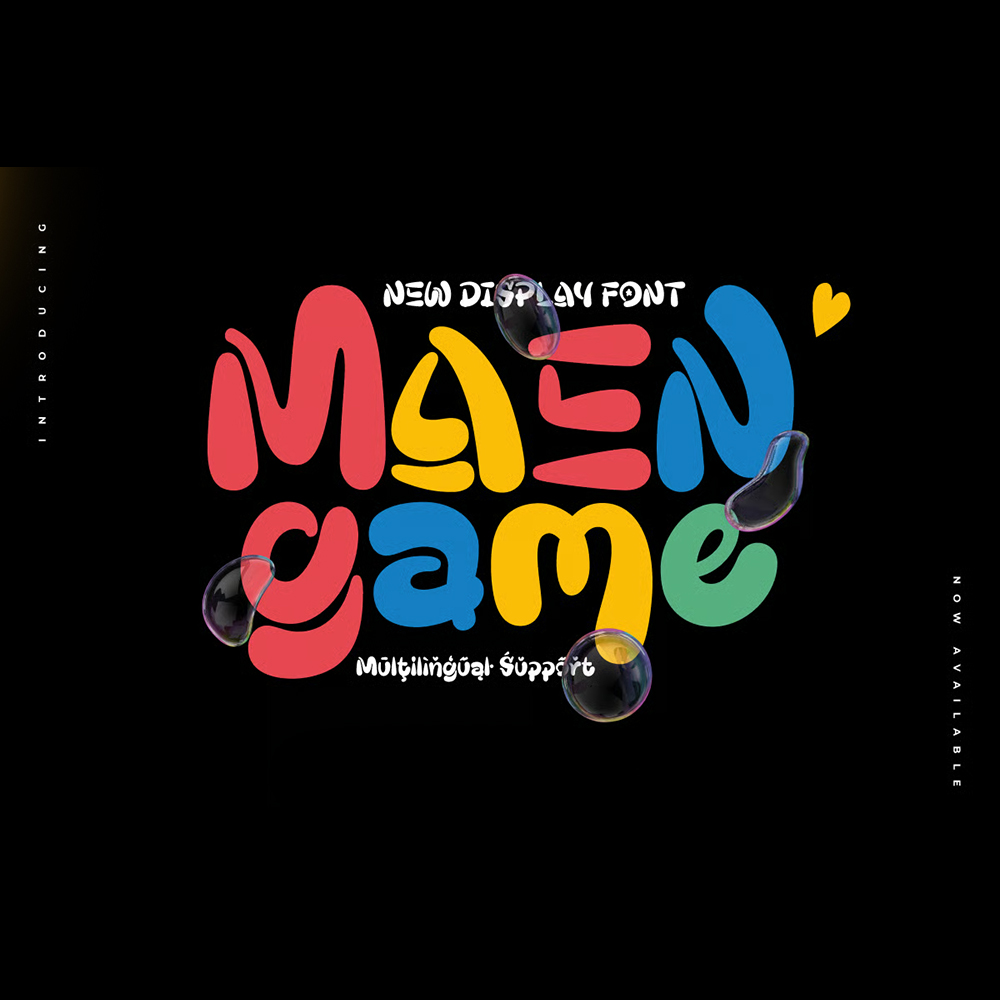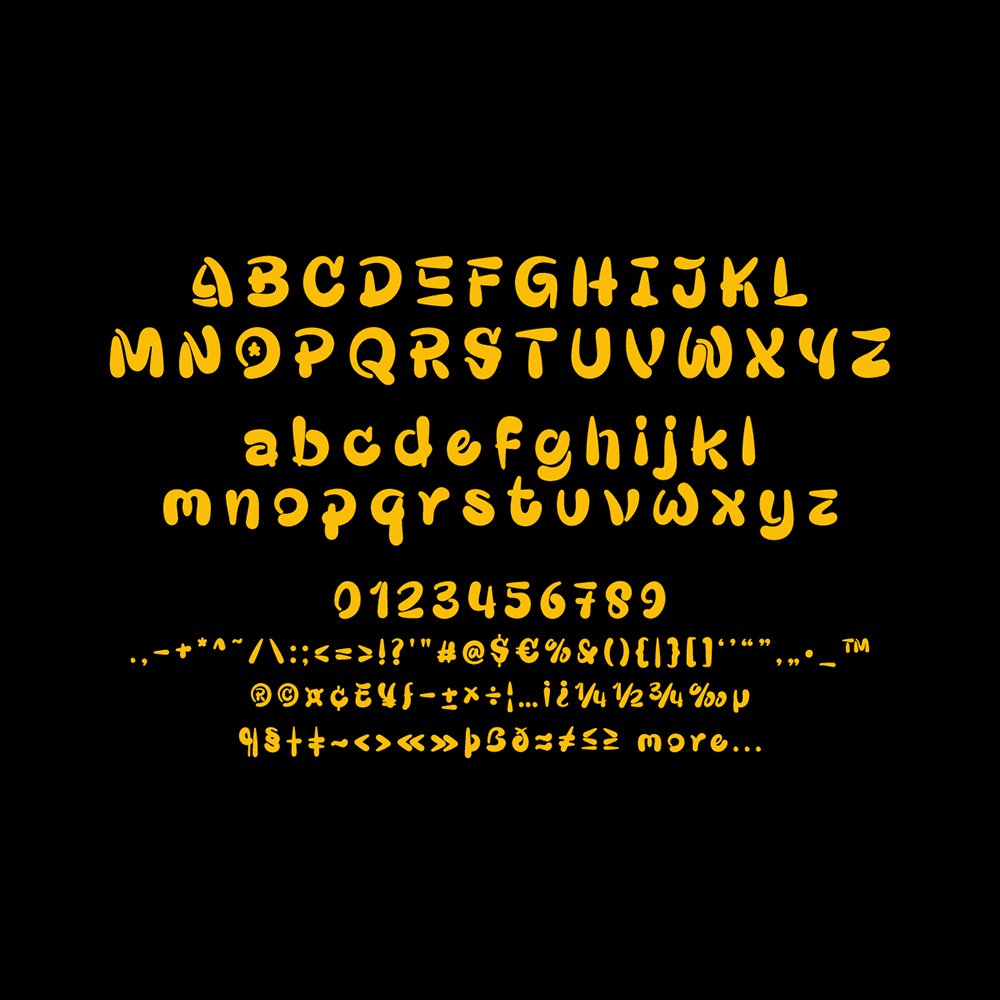
دانلود فونت انگلیسی Maengame Font
فونت پرمیوم و انگلیسی Maengame Font فقط یک فونت نیست؛ بلکه دروازهای به دنیایی از شادی و قدرت در طراحیهای شماست. Maengame با تمهای نمایشی چشمنواز و سبک بازی قوی، جلوهای منحصر به فرد به پروژههای شما میبخشد. با طراحی حبابی شکل، به هر شخصیت جلوهای بازیگوشانه ببخشید و عنصری بازیگوشانه به هر حرف اضافه کنید.
مزایای استفاده از فونت لاتین Maengame Font چیست؟